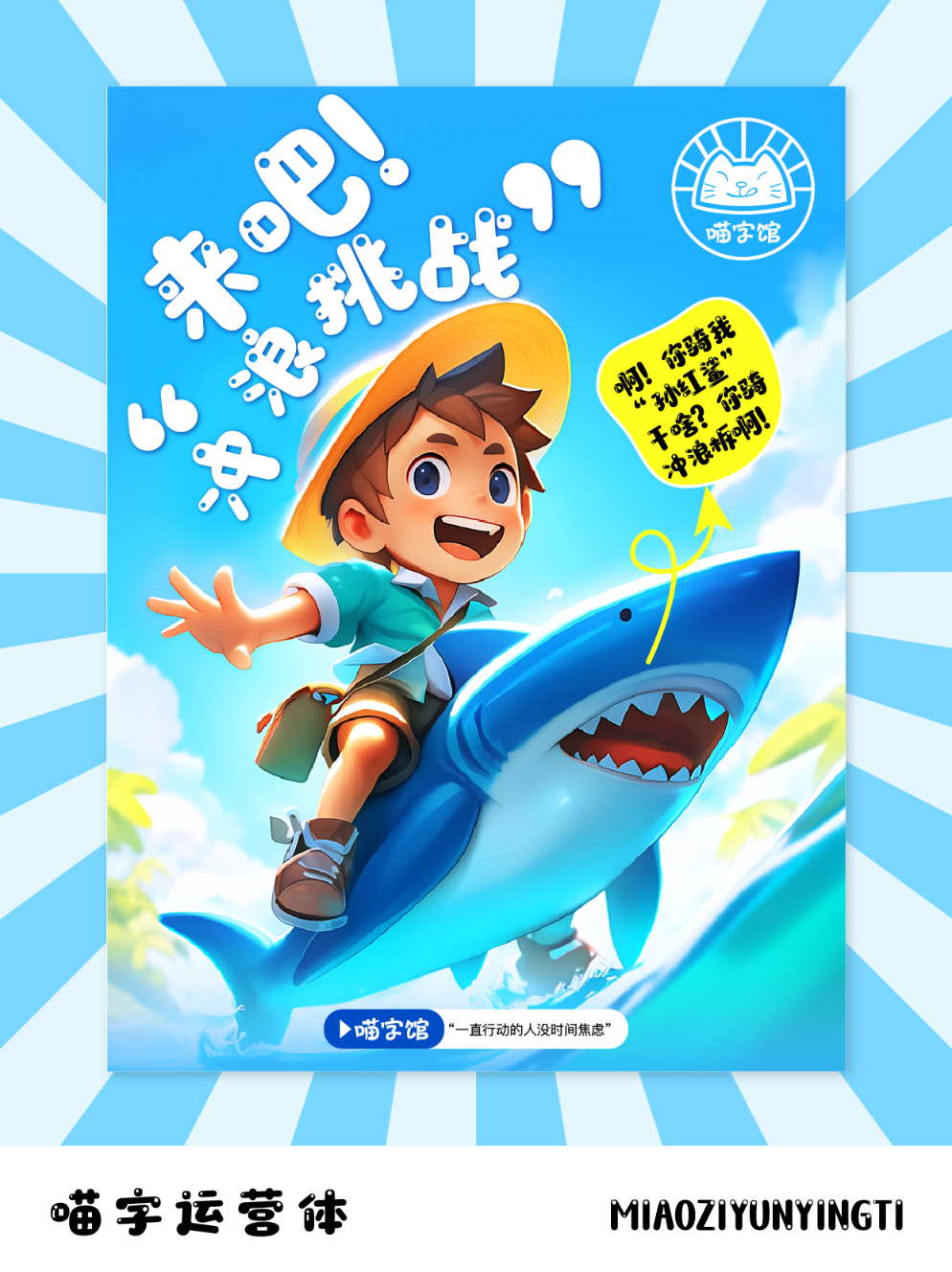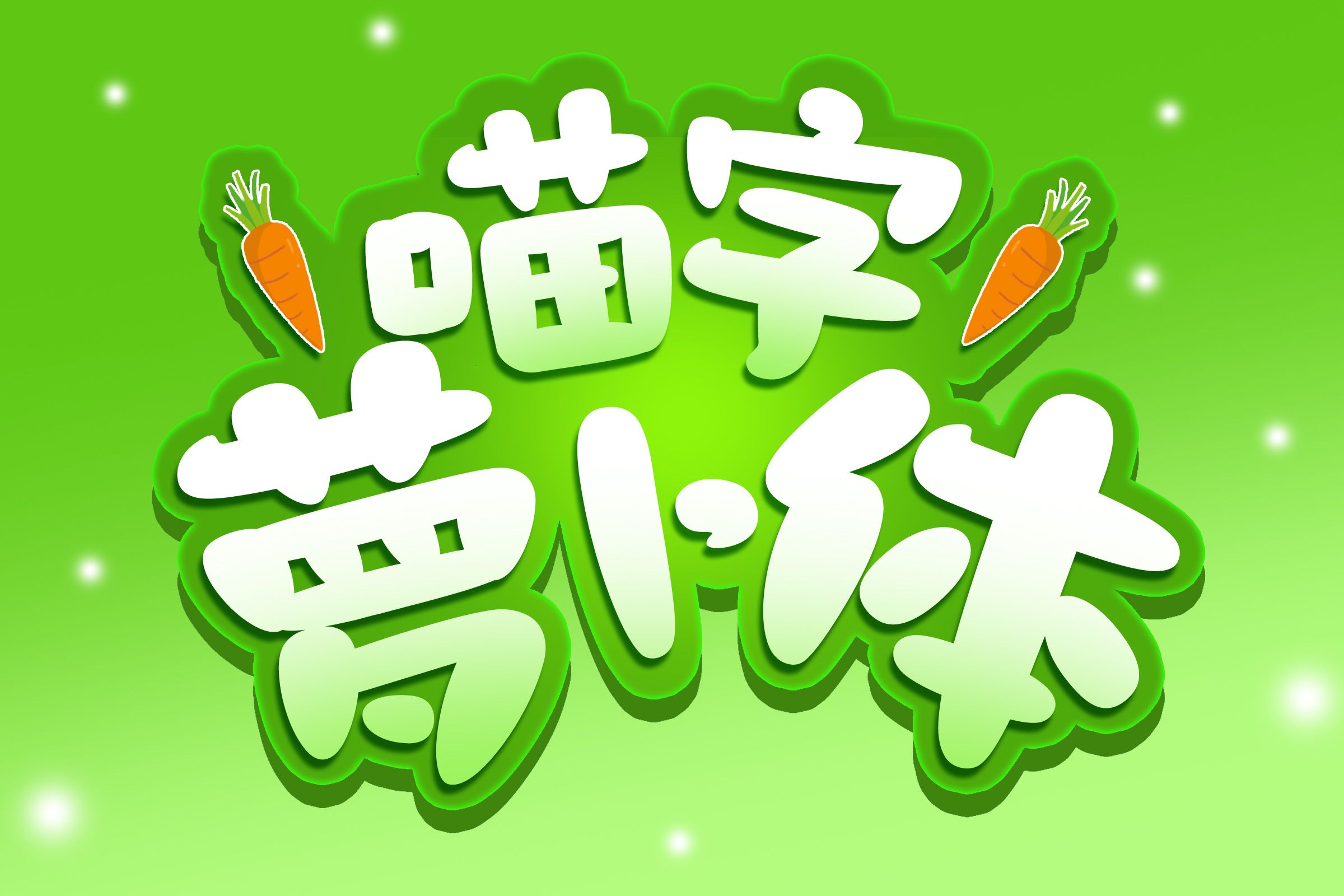
综艺视觉创意新宠:四款喵字系列定制字体解锁品牌表达新维度
在综艺节目视觉呈现日益追求个性化的当下,字体设计已成为强化品牌记忆、传递情感温度的关键元素。本文精选四款喵字系列定制字体,从商业运营到场景化表达,为综艺内容创作提供多元化的视觉解决方案。
一、喵字运营体
专为社企运营场景打造的喵字运营体,以几何化结构构建理性美学体系。其模块化设计兼顾多语言适配性,在综艺冠名商品牌露出、信息栏排版等场景中,既能保持品牌调性统一,又通过微倾斜的笔画动态打破常规商业字体的刻板印象。某美食综艺中,该字体成功将快餐品牌视觉识别度提升40%,印证其在商业转化场景中的实效性。
二、喵字萝卜体
作为国内首款农产品主题定制字体,萝卜体创新性地将蔬菜形态解构重组。圆润的笔画末端模拟萝卜肉质,中宫收紧的设计暗合植物生长张力,在《向往的生活》等田园综艺中,该字体与自然场景形成奇妙共振,使农产品赞助商的视觉传达更具人文温度。
三、喵字海报体
突破传统字库的静态框架,海报体通过0.8-1.2倍的笔画粗细对比制造视觉韵律,其独有的"错位衔接"技术让标题排版呈现手写涂鸦的随机感。在《这!就是街舞》等青年文化综艺中,该字体成功承载了涂鸦艺术与赛博朋克的混搭美学,单期节目弹幕提及率达2.3万次。
四、喵字文案体
将书法飞白与无衬线结构进行分子级融合,文案体创造出独特的"呼吸感"字效。其0.618的黄金中宫比例,使长文本阅读效率提升25%,在《朗读者》等文化类综艺字幕系统中,该字体通过笔画的虚实过渡,精准传递文字背后的情感张力。
从商业转化到情感共鸣,喵字系列字体通过垂直场景的深度开发,重新定义了综艺视觉语言的表达边界。当字体设计开始承载品牌战略与情感价值,这些风格独特的定制字库字体,正在成为内容创作者的新一代视觉武器。